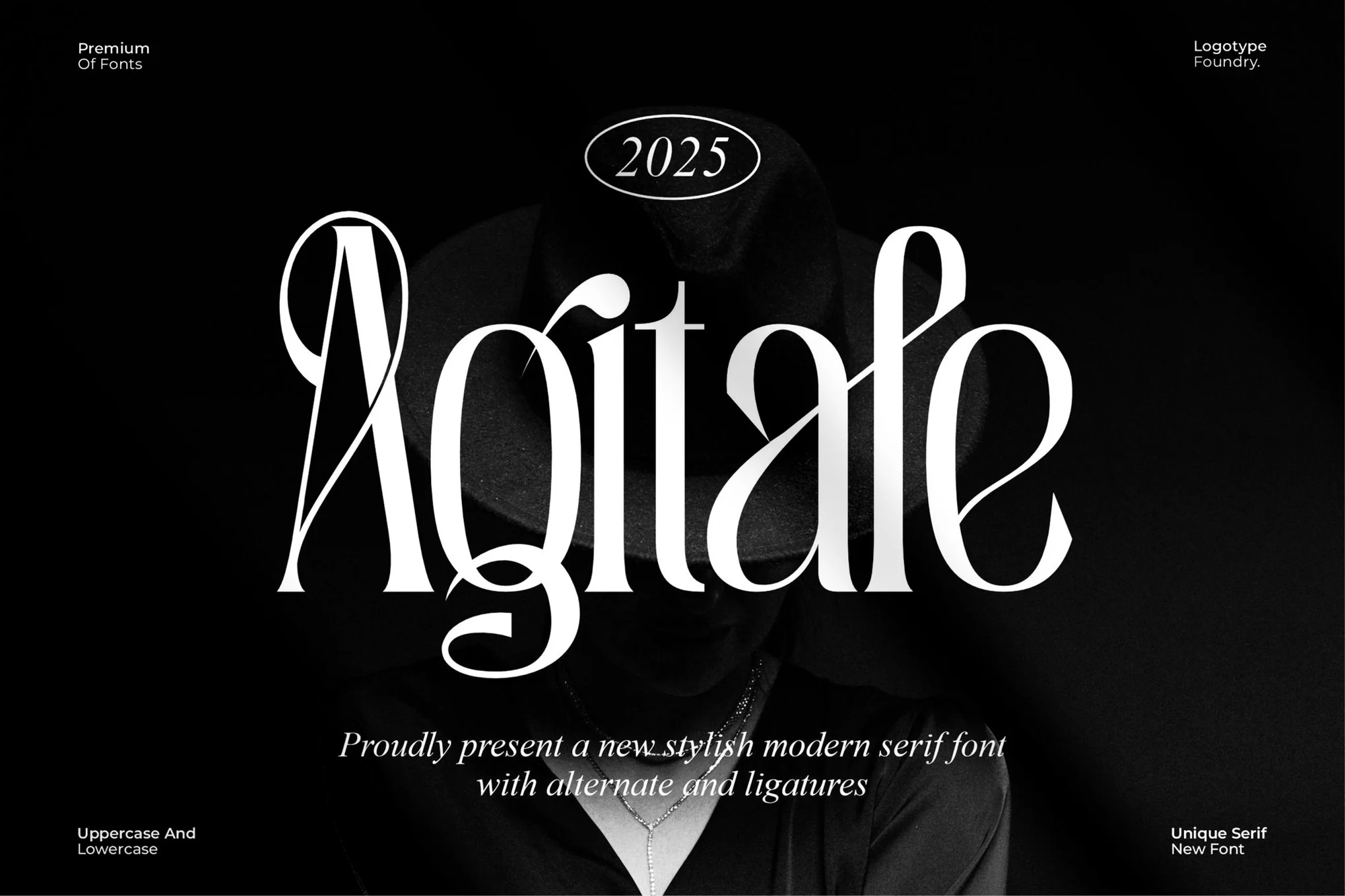
فونت Agitafe یک فونت سریف (Serif) مدرن، فانتزی و نمایشی است که حالتی پر جنبوجوش، ترندی و بانمک دارد. این فونت با داشتن شخصیتی منحصربهفرد با تم چوبی (wood theme)، انتخابی عالی برای طراحیهای خاص و چشمنواز است.
- دارای حروف بزرگ و کوچک
- پشتیبانی از اعداد و علائم نگارشی